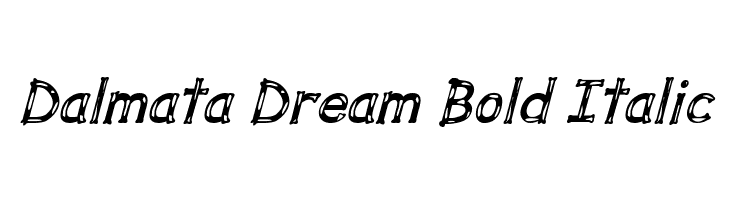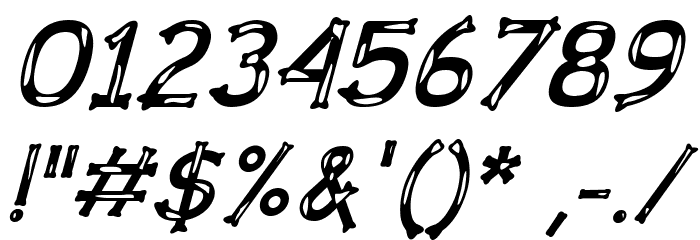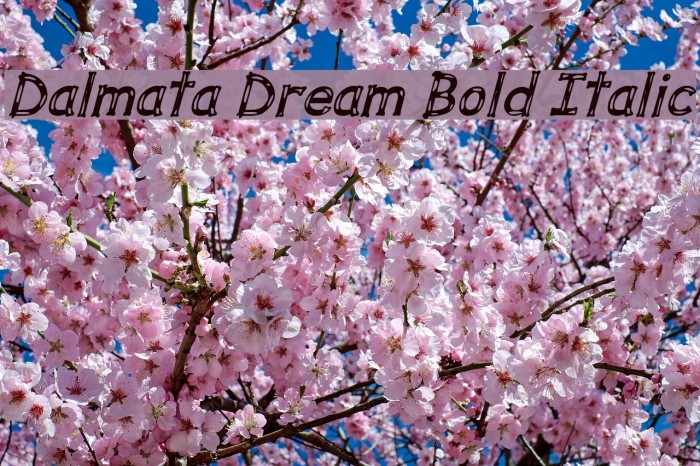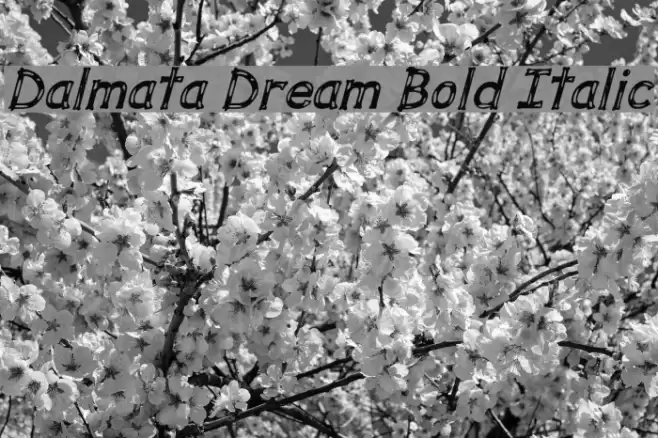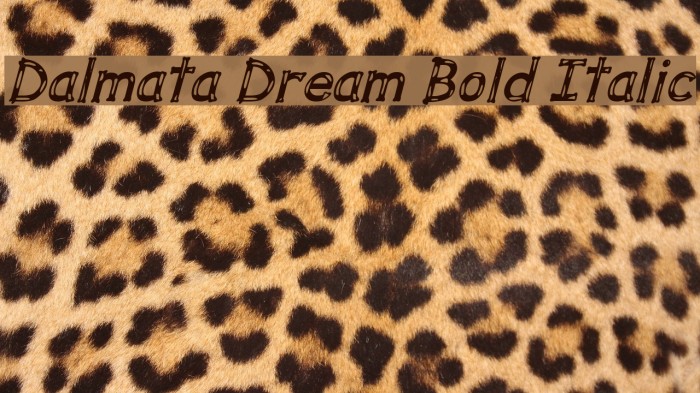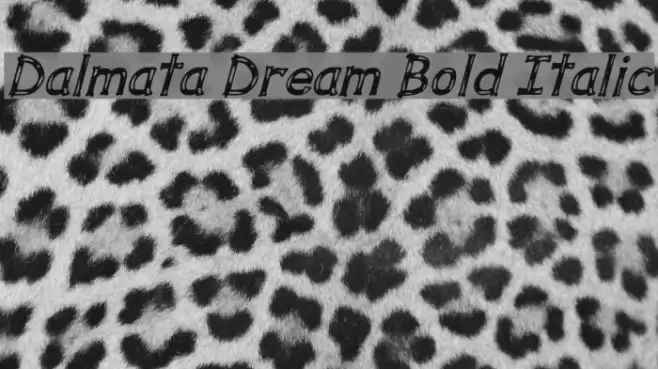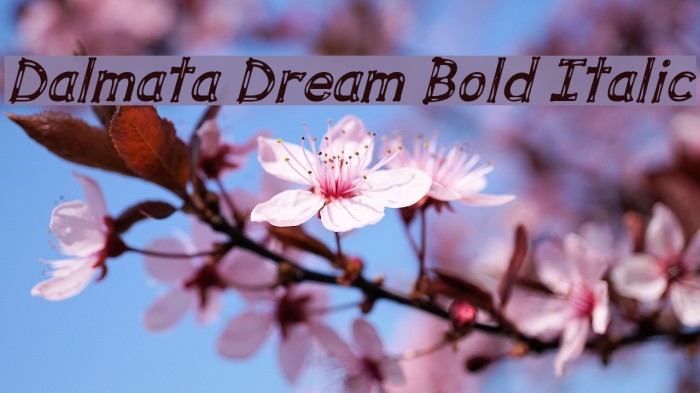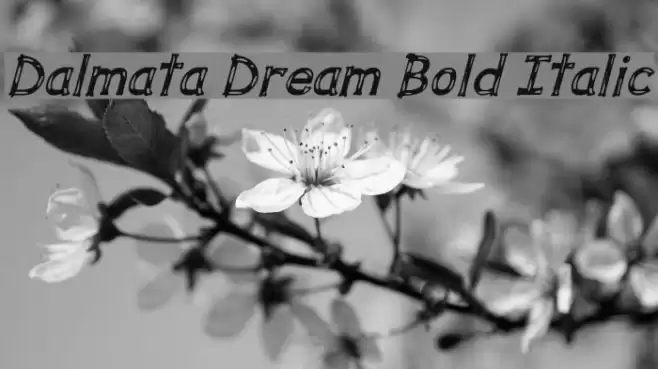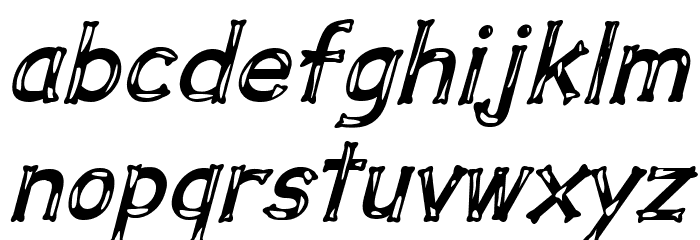
Dalmata Dream Bold Italic Font
| مشاريع مقترحة | Ideal for creative projects such as posters, album covers, children's books, and branding materials that require a fun and dynamic touch. |